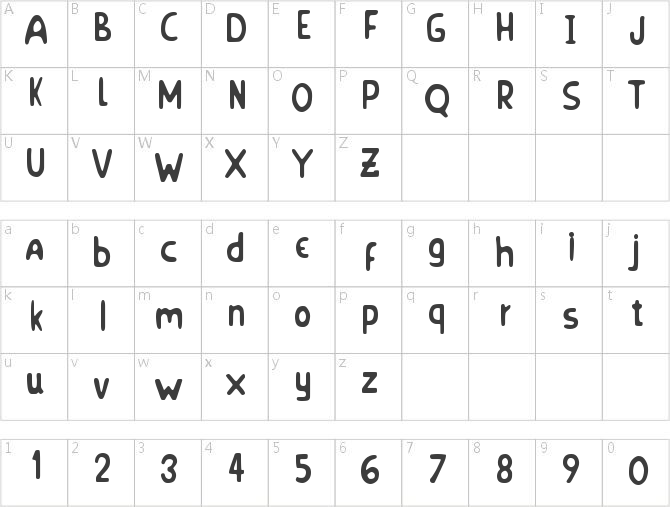
字體名稱: Horny_V
Horny_Village_SEGUNDA
Horny_Village_SEGUNDA介紹
Horny_Village_SEGUNDA字體字庫是一款讓人賞心悅目、百看不厭的英文字體,適合各類廣告和產品包裝設計應用,字體大小0.05MB,格式為ttf字體,上傳用戶是小李哥/,作者/版權方為未知